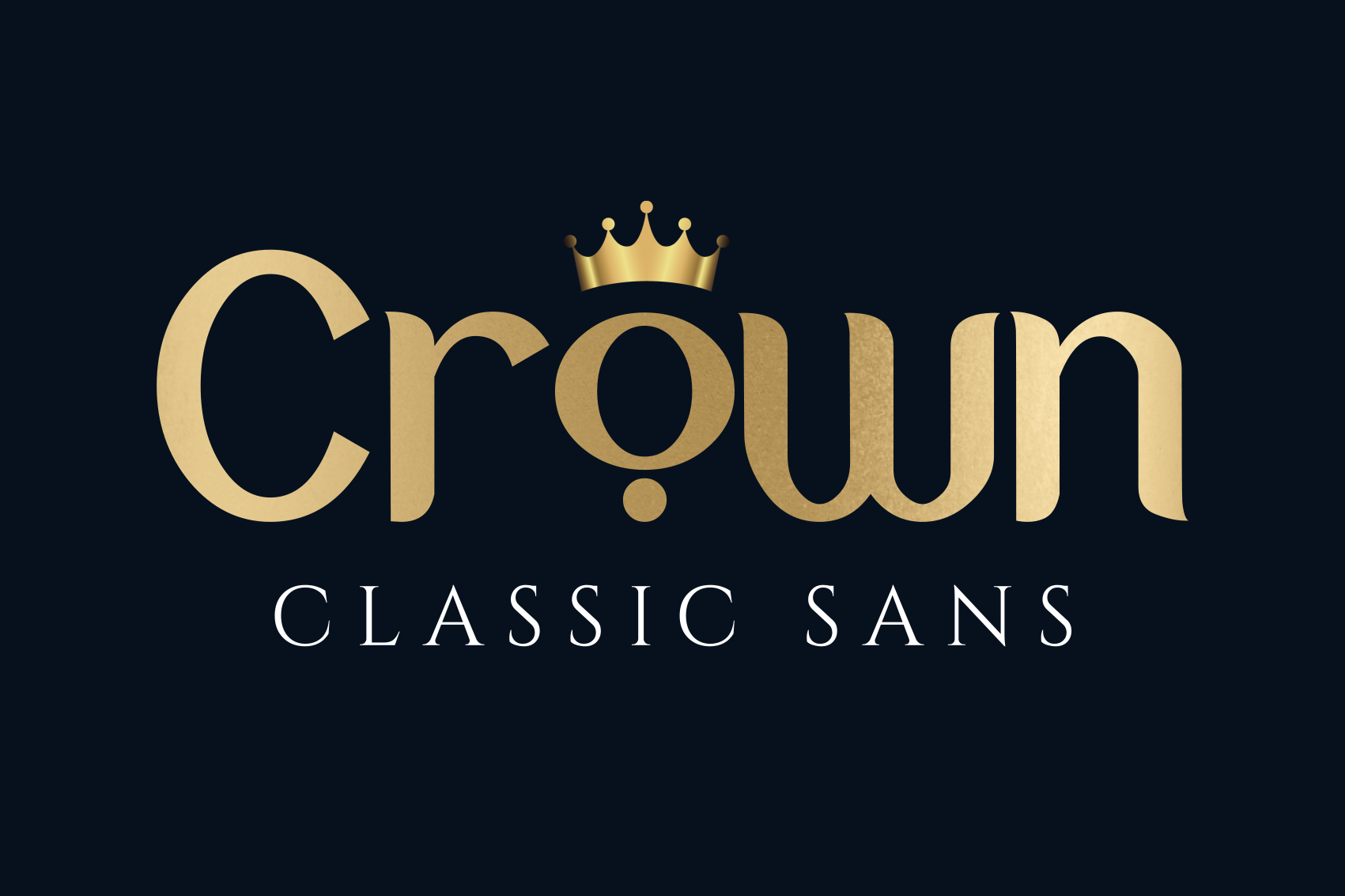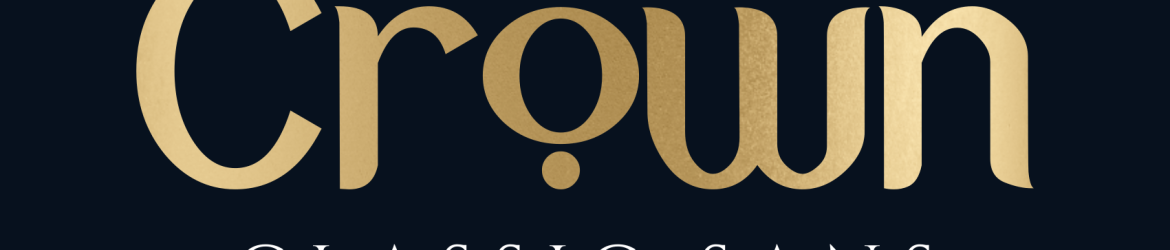
Crown Typeface – Download Grátis
Crown Typeface é uma tipografia sans-serif que surge com duas configurações de letras maiúsculas e minúsculas, algumas alternativas e ligaturas. É ideal para várias aplicações designísticas como identidade de marca, design de outdoors, embalagens, sites ou desenhos de destaque, edições, headlines e logotipos. Este conjunto de fontes suporta uma ampla gama de usos, desde o design de editoriais até a criação de elementos visuais para aplicações digitais. Crown apresenta um design elegante e moderno que complementará perfeitamente qualquer projeto visual. Ideal tanto para os designers como para quem busca personalidade em suas apostas gráficas. Sempre pronta para dar vida aos seus projetos, seja na web ou no papel.